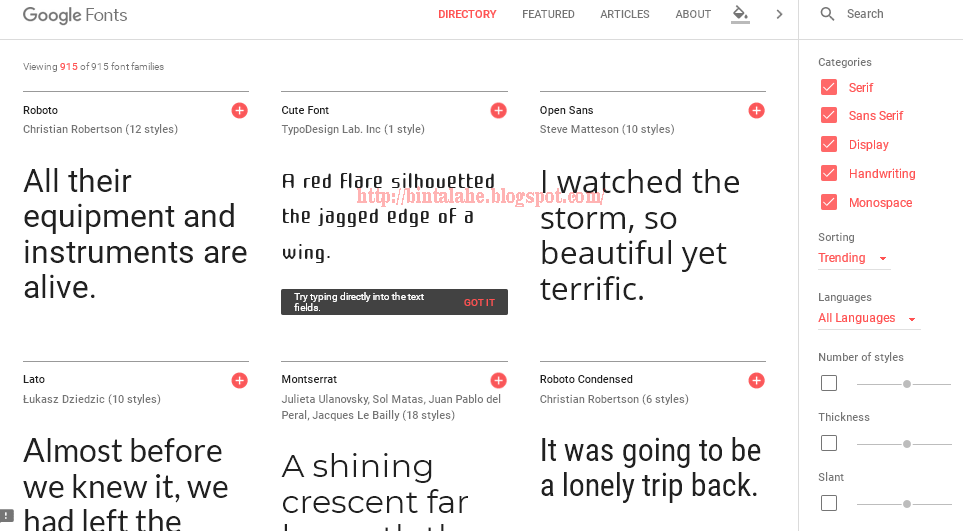
10 советов по типографике в веб-дизайне
Коммуникация играет жизненно важную роль в дизайне – важно установить четкую связь между веб-сайтом и пользователем и помочь им достичь своих целей. Когда мы говорим об общении в контексте веб-дизайна, мы обычно подразумеваем текст. Типографика играет жизненно важную роль в этом процессе:
Более 95% процентов информации в Интернете представлено в виде письменного языка.
Хорошая типографика делает чтение непринужденным, в то время как плохая типографика отталкивает пользователей. Как утверждает Оливер Райхенштейн в своей статье “Веб-дизайн – это 95% типографики”:
Оптимизация типографики – это оптимизация читабельности, доступности, удобства использования (!), общего графического баланса.
Другими словами, оптимизируя типографику вы также оптимизируете ваш пользовательский интерфейс. В этой статье я предоставлю ряд правил, которые помогут улучшить читаемость и разборчивость вашего текстового контента.
Использование более трех разных шрифтов заставляет сайт выглядеть неструктурированным и непрофессиональным. Имейте в виду, что слишком много размеров и стилей шрифта одновременно также могут разрушить любой макет. Чтобы предотвратить подобную ситуацию, попробуйте ограничить количество семейств шрифтов до минимума В общем, ограничьте количество семейств шрифтов до минимума (два – это много, часто бывает достаточно одного) и придерживайтесь их на всем веб-сайте. Если вы используете более одного шрифта, убедитесь, что семейства шрифтов дополняют друг друга в зависимости от ширины их символов. Ниже приведен пример сочетаний шрифтов. Сочетание Georgia и Verdana (слева) имеет сходные значения, которые создают гармоничное соединение. Сравните это с парой Baskerville и Impact (справа), где тяжелый вес шрифта Impact значительно затмевает другой шрифт. Убедитесь, что семейства шрифтов дополняют друг друга, основываясь на ширине их символов
Попробуйте использовать стандартные шрифтыВ сервисах внедрения шрифтов (например, Google Web Fonts или Typekit) есть много интересных шрифтов, которые могут придать вашим проектам что-то новое, свежее и неожиданное. Они также очень просты в использовании. Возьмем, например, Google:
- Выберите любой шрифт, например, Open Sans.
Так что может пойти не так? На самом деле, этот подход имеет одну серьезную проблему – пользователи более знакомы со стандартными шрифтами и могут читать их быстрее. Если на вашем веб-сайте нет особой необходимости в использовании специального шрифта, например, для целей брендинга или создания впечатляющего опыта, обычно, лучше всего использовать системные шрифты. Беспроигрышный вариант – использовать системные шрифты: Arial, Calibri, Trebuchet и т.д. Имейте в виду, что хорошая типографика привлекает читателя к контенту, а не к самому шрифту.
Наличие правильного количества символов в каждой строке является ключом к удобочитаемости вашего текста. Не должно быть так, чтобы ваш дизайн диктовал вам ширину текста. Это также должно быть вопросом читабельности. Посмотрите этот совет по удобочитаемости и длине линии от Института Баймарда:
“У вас должно быть около 60 символов на строку, если вы хотите получить хороший опыт чтения. Наличие правильного количества символов в каждой строке является ключом к читабельности вашего текста”.
Если линия слишком короткая, глазу придется слишком часто возвращаться, нарушая ритм читателя. Если строка текста слишком длинная, пользователю будет сложно сосредоточиться на тексте. Изображение: Material Design Для мобильных устройств вы должны использовать 30–40 символов в строке. Ниже приведен пример двух сайтов, просматриваемых на мобильном устройстве. Первый использует 50-75 символов в строке (оптимальное количество символов в строке для печати и для компьютера), а второй использует оптимальные 30-40 символов.
Изображение: Usertesting В веб-дизайне вы можете добиться оптимального количества символов в строке, ограничивая ширину ваших текстовых блоков используя em (относительную единицу измерения) или пиксели.
Пользователи получат доступ к вашему сайту с устройств с различными размерами экрана и разрешениями. Большинство пользовательских интерфейсов требуют текстовые элементы различных размеров (текст кнопок, метки полей, заголовки разделов и т. д.). Важно выбрать шрифт, который хорошо работает в разных размерах, чтобы обеспечить читаемость и удобство использования в любом размере. Шрифт Roboto от Google
Используйте шрифты с различимыми буквамиВо многих шрифтах слишком легко перепутать аналогичные формы букв, в частности “i” и “L” (как видно на изображении ниже), и маленькие расстояния между буквами, например, когда “r” и “n” выглядят как “m”. Поэтому, выбирая шрифт, обязательно проверяйте его в разных контекстах, чтобы убедиться, что это не вызовет проблем у ваших пользователей.
6. Избегайте печатать все прописными буквамиТекст, целиком написанный прописными буквами – отлично подходит в контекстах, которые не подразумевают чтение (например, акронимы или логотипы), но, когда ваше сообщение подразумевает чтение, не заставляйте своих пользователей читать текст, написанный заглавными буквами. Как уже упоминалось Майлсом Тинкером, в его знаковой работе “Легкость печати”, текст целиком написанный в верхнем регистре значительно замедляет скорость просмотра и чтения по сравнению с нижним регистром.
7. Не уменьшайте расстояние между строчкамиВ типографике у нас есть специальный термин для расстояния между двумя строками текста – лидинг (leading) или межстрочный интервал.
Вот пример:
p {семейство шрифтов:Montserrat,Arial,sans-serif; } В этом фрагменте мы настроили текст абзаца так, чтобы сначала отображался шрифт Montserrat. Если на устройстве пользователя не установлен шрифт Montserrat, вместо него будет использоваться шрифт Arial. Вы можете включить более двух шрифтов, если хотите, и использовать разные шрифты для основного текста, заголовков и заголовков.